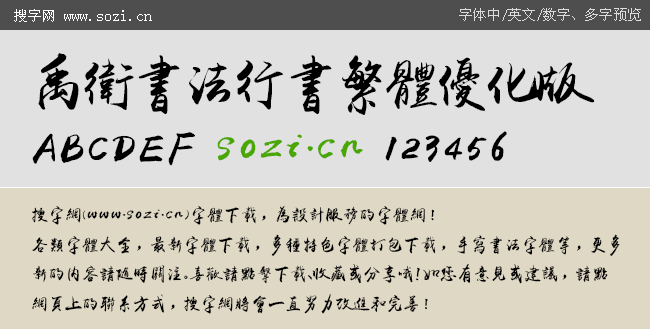
禹衛(wèi)書法行書繁體優(yōu)化版
搜字網(wǎng)給大家提供一款禹衛(wèi)書法行書繁體優(yōu)化版中文書法字體下載。該字體是一款古風(fēng)味道十足的行書書法字體,字形飄逸大方,書法韻味十足。適合包裝設(shè)計(jì)、海報(bào)設(shè)計(jì)、畫冊設(shè)計(jì)等廣告設(shè)計(jì)場合使用。